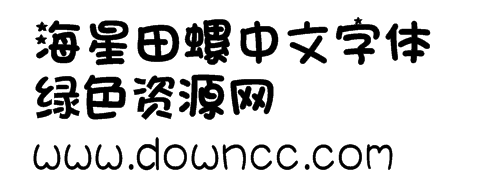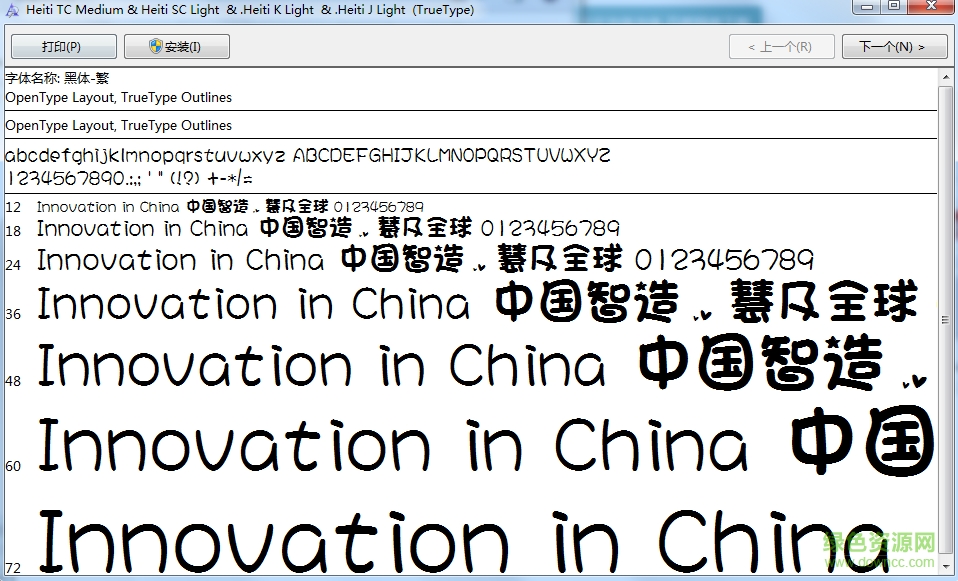
海星田螺中文字體是一款充滿可愛星星圖案的藝術(shù)字體,卡通風(fēng)味十足很有童真童趣之感,喜歡的朋友快來綠色資源網(wǎng)免費(fèi)下載吧!
海星田螺體字體是一款創(chuàng)意圓潤藝術(shù)字體,本作品可用于出版印刷字體、廣告設(shè)計(jì)字體、網(wǎng)頁設(shè)計(jì)字體、包裝設(shè)計(jì)字體、 屏幕顯示字體等。
字體在軟件中的名稱為:海星田螺體。
海星田螺讓人感覺很清新很恬靜,是一款不可多得的卡通字體,字里行間充滿隨意灑脫之感,猶如孩子的天行。